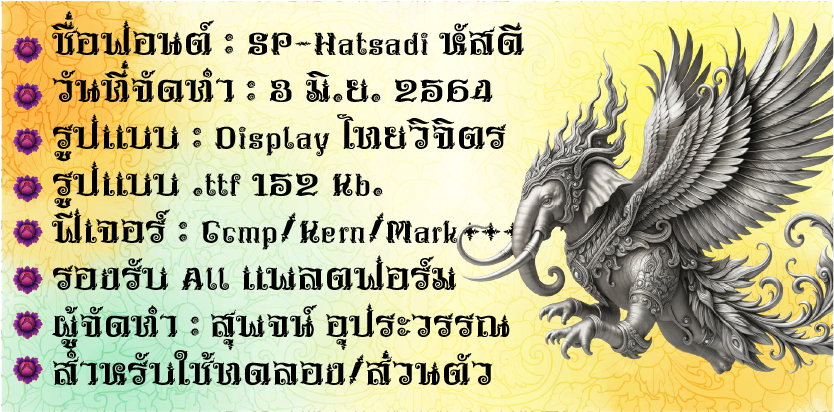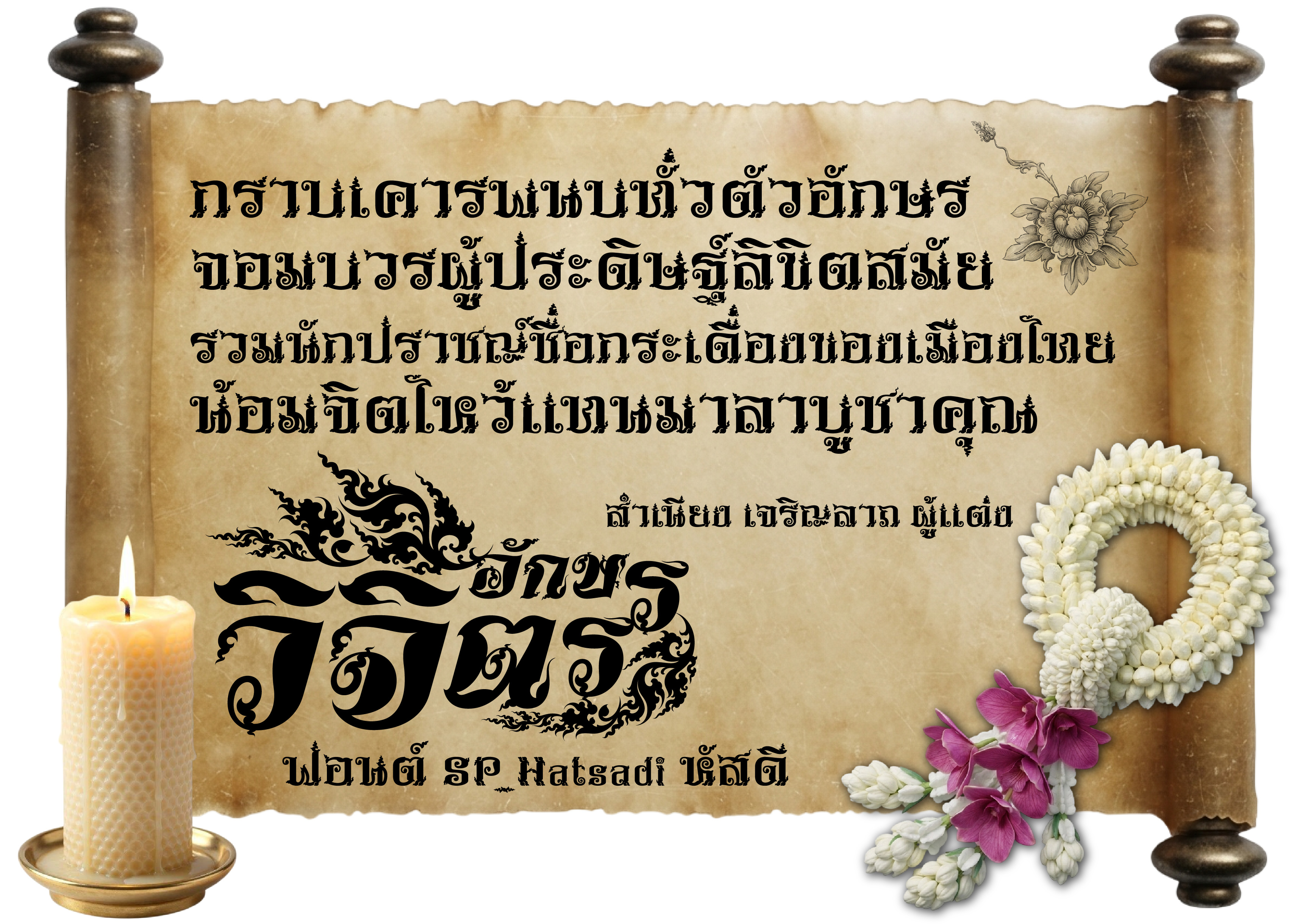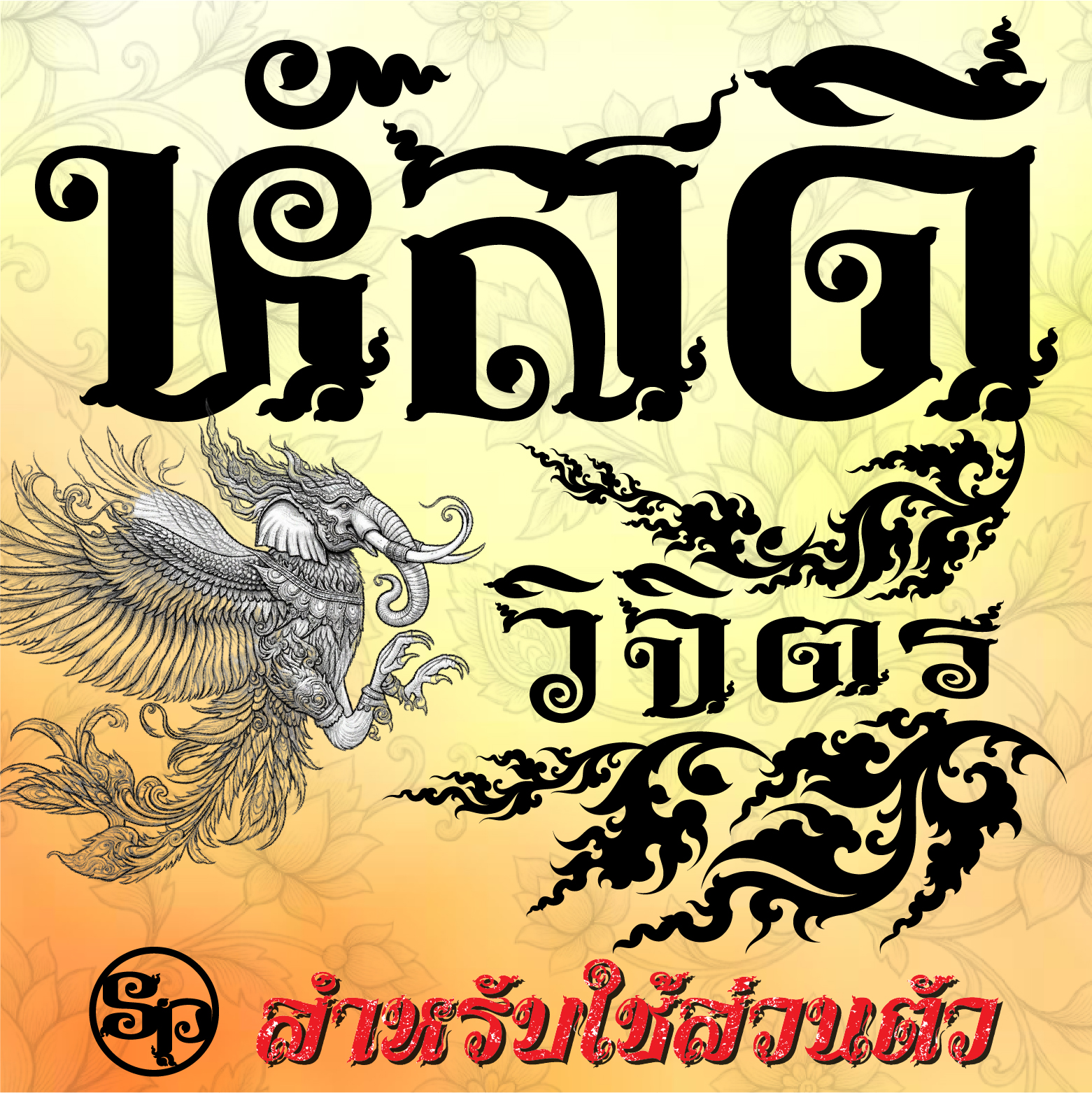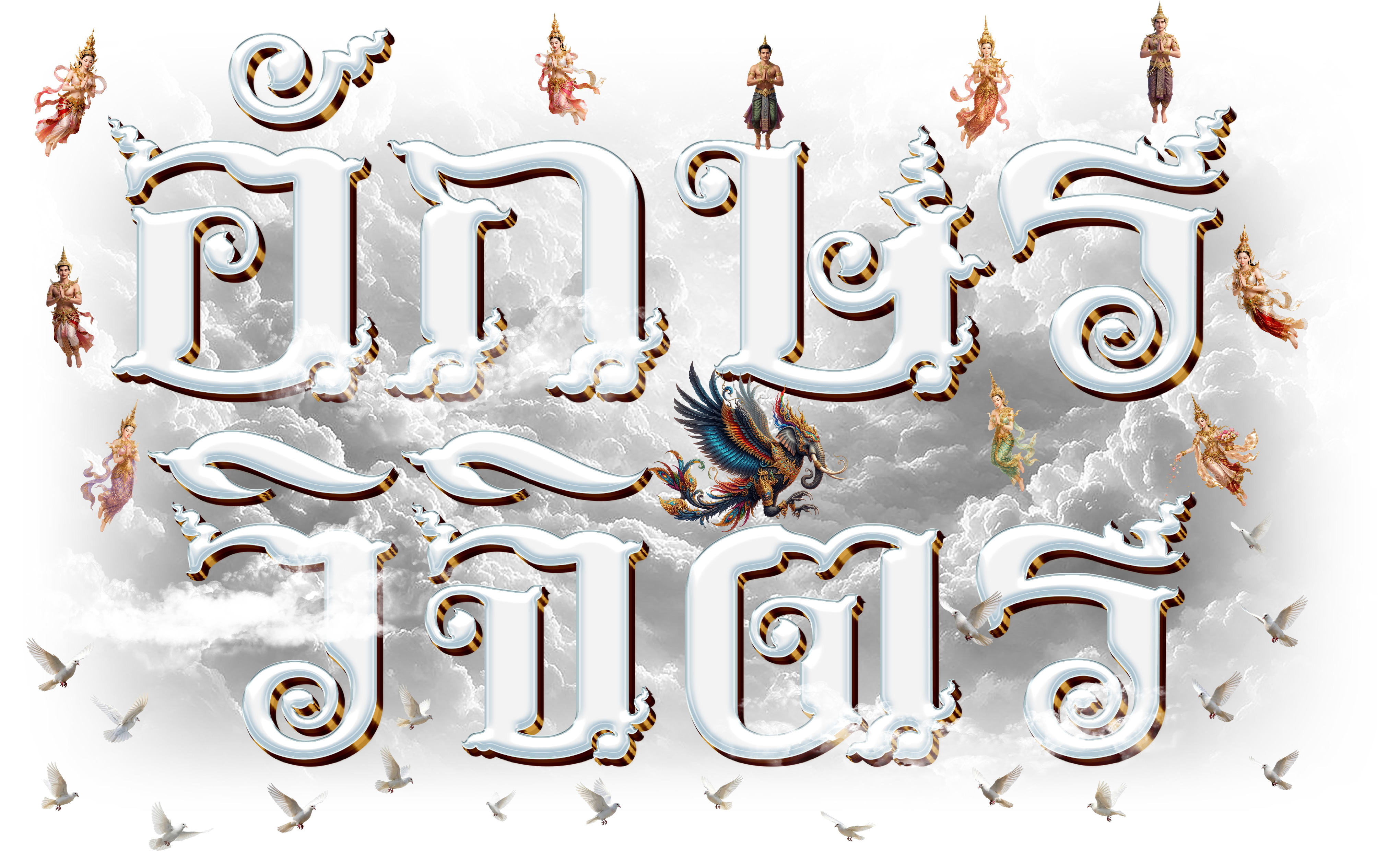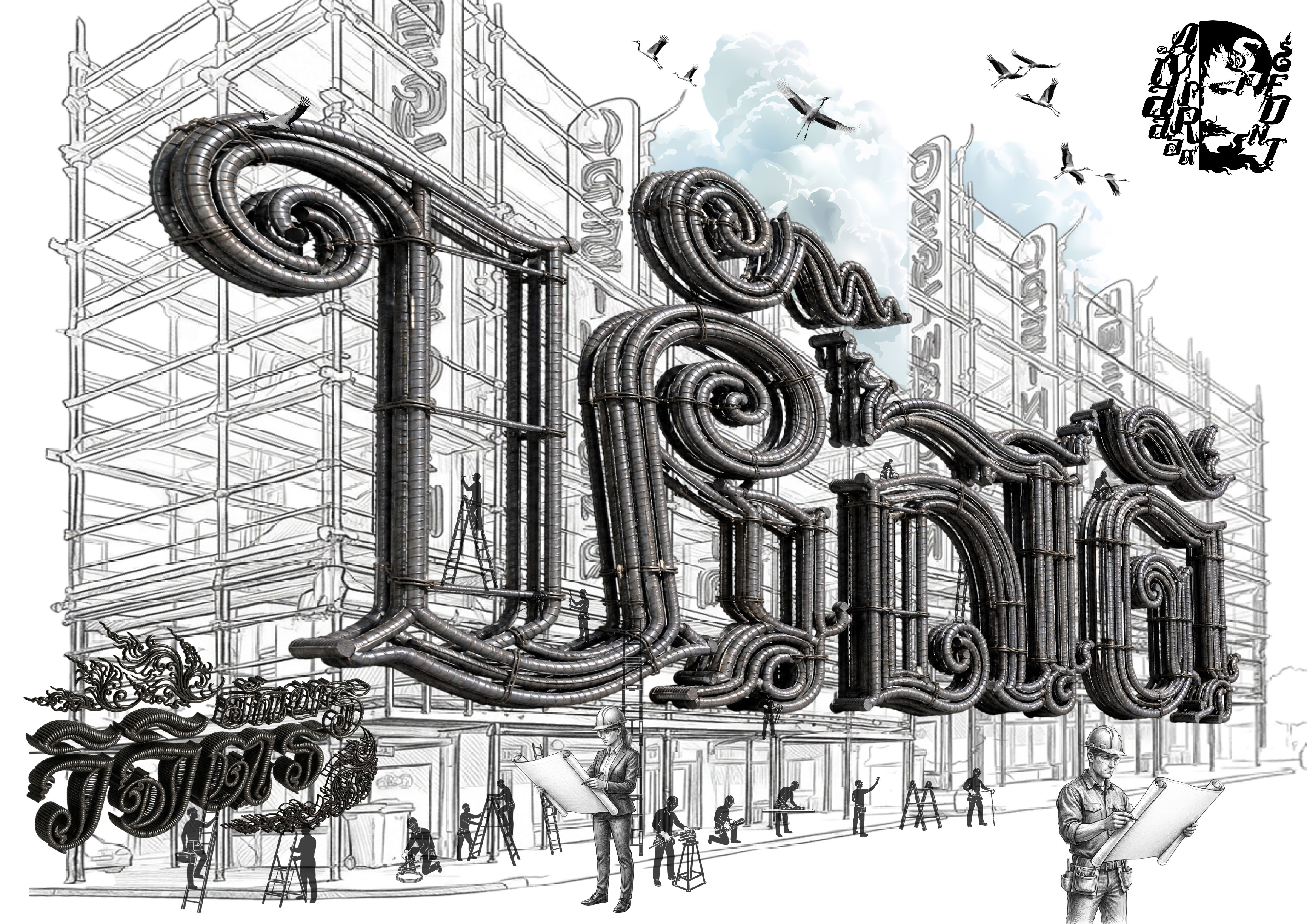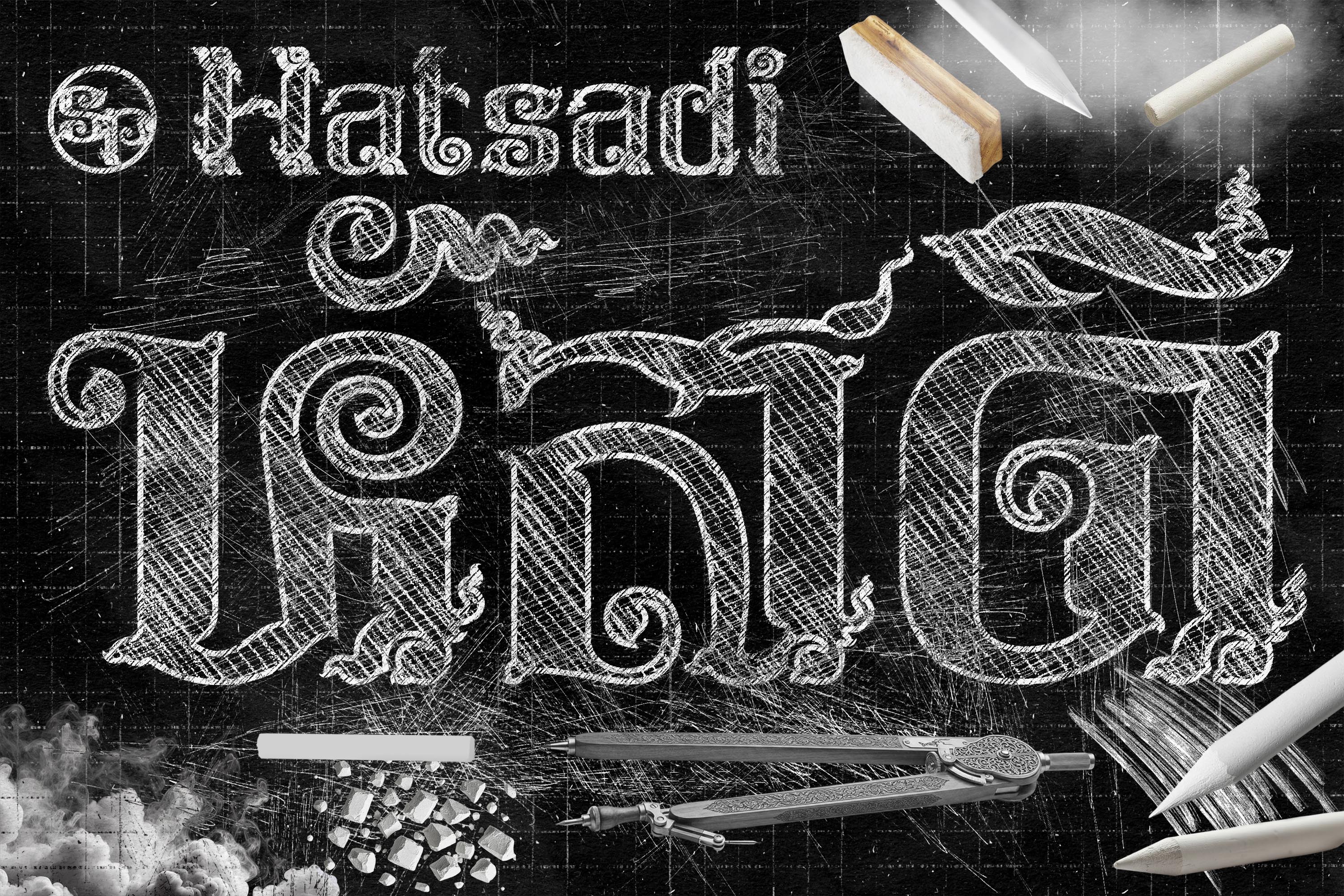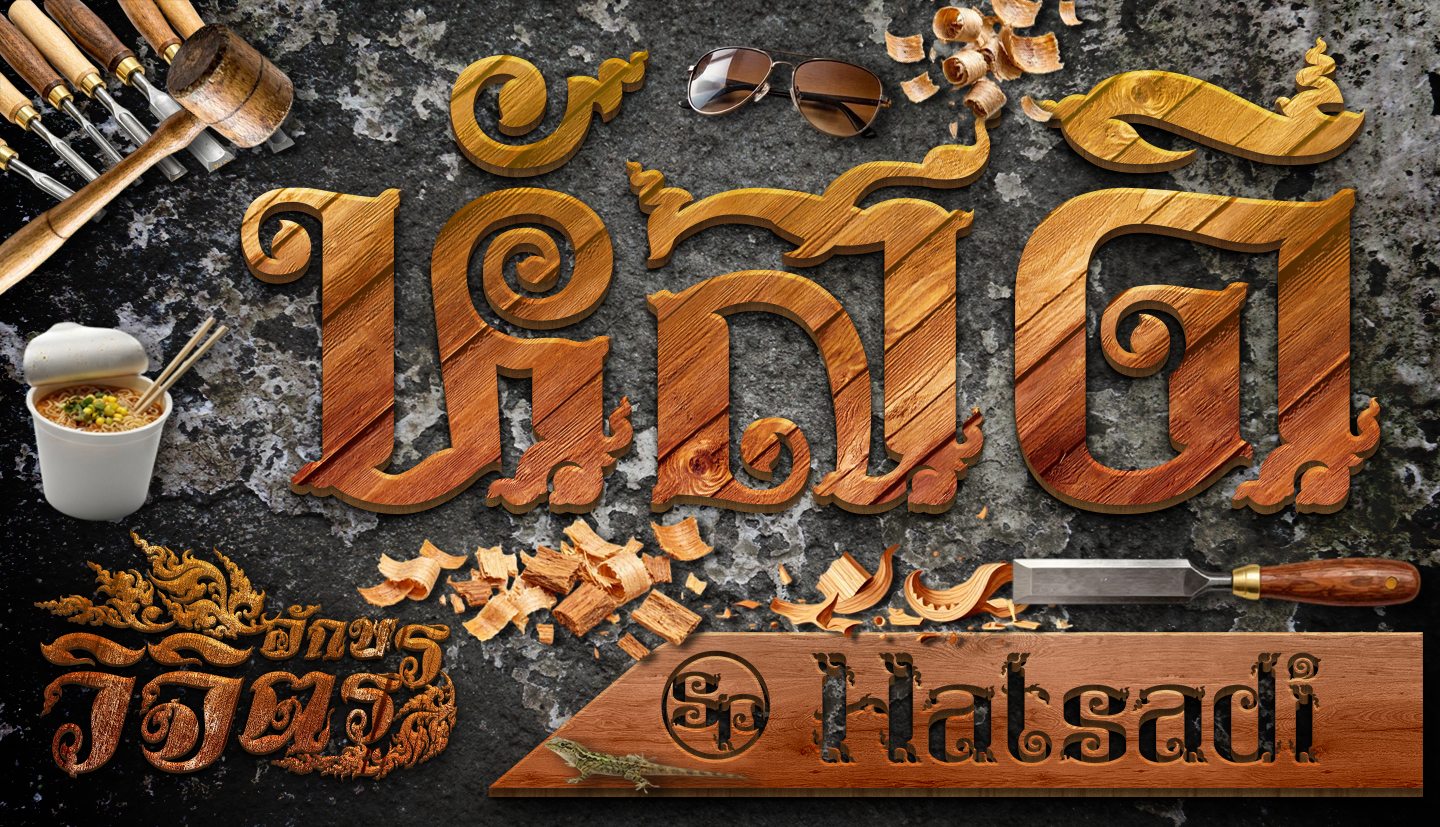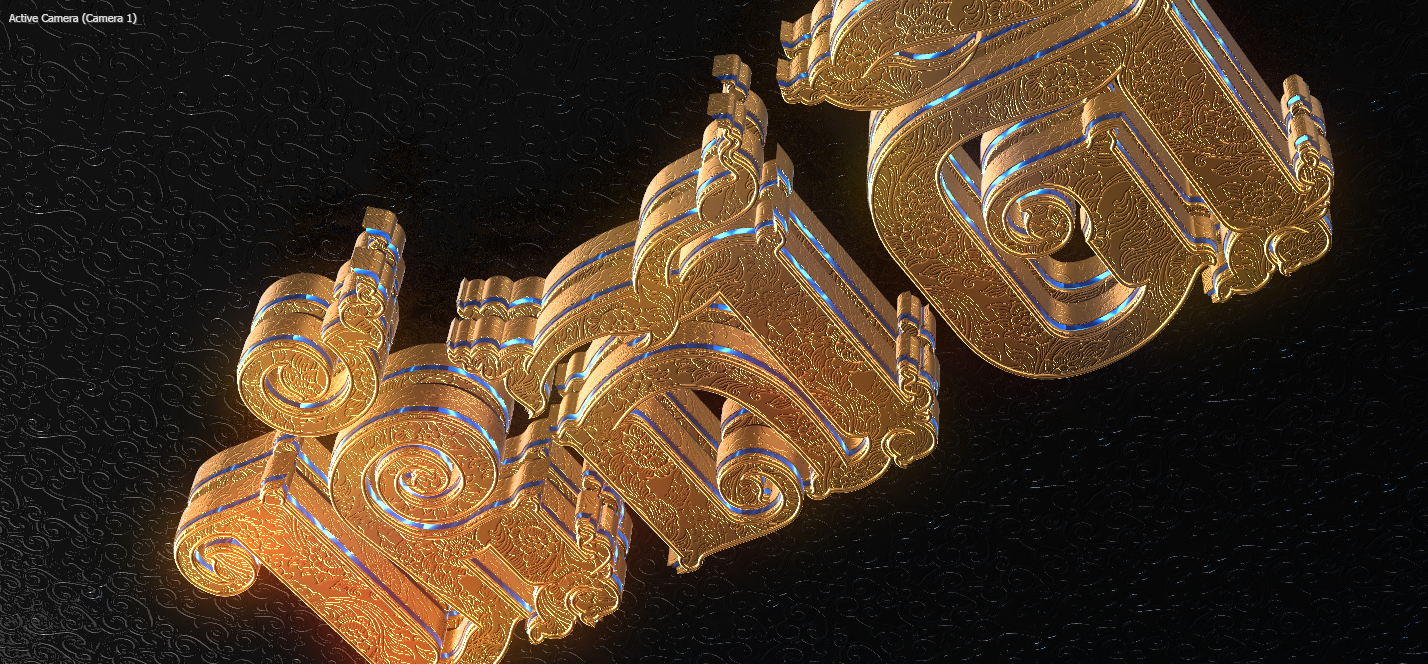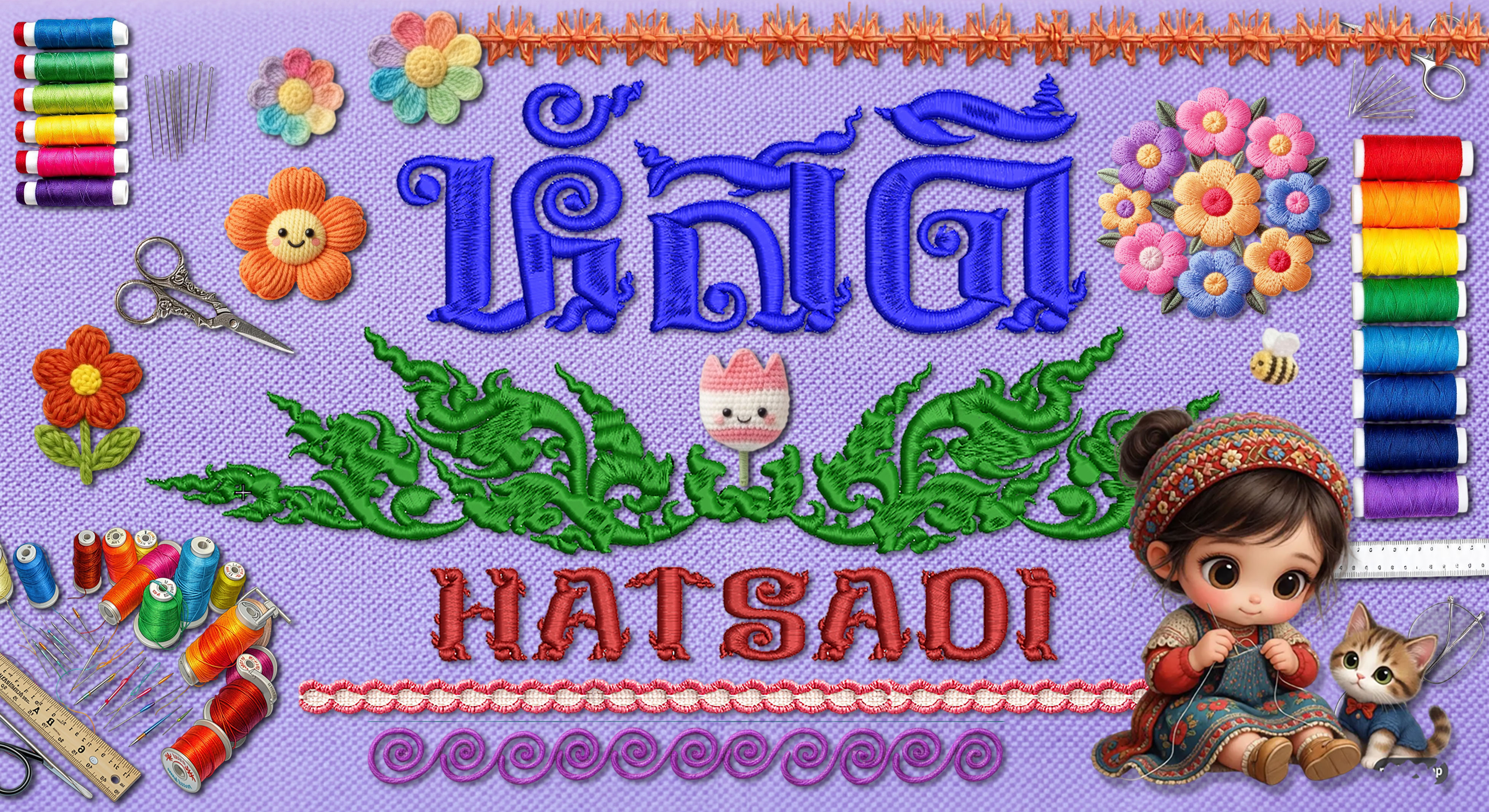
SP_Hatsadi หัสดี
SP_Hatsadi หัสดี เป็นฟอนต์ที่อยู่ในโครงการอักษราสูตรไทยวิจิตร มุ่งเน้นการออกแบบลายเส้นให้กลมกลืนกับศิลปะลวดลายไทย
จัดรูปแบบอักษรให้เป็นเอกลักษณะเฉพาะตัว เข้ากันกับชุดอักษรนั้นๆ รวมถึงอักษรภาษาอังกฤษและสัญลักษณ์อื่นๆครบถ้วนบริบูรณ์
พร้อมใส่ฟีเจอร์ (แก้สระลอย-ล็อกเป้าเข้าพิกัด) เพื่อความสวยงามและลงตัว ไม่ว่าจะเป็นช่องไฟ สระวรรณยุกต์ ชั้นล่างชั้นบน
และแยกนิคหิตเพื่อการใช้พิมพ์ภาษาบาลีไห้ถูกต้องตามหลักไวยากรณ์ ภายในฟอนต์ๆเดียว (Microsoft-Adobe ต้องเปิดค่ารองรับ)